Lựa chọn các font chữ thiết kế đẹp, phù hợp đem lại giá trị không hề nhỏ trong việc nâng cao trải nghiệm người dùng và gia tăng tỷ lệ khách hàng quay lại. Nếu bạn chuẩn bị thiết kế website và cần chọn 1 font đẹp cho web, hãy cùng theo dõi bài viết dưới đây
1. Phân biệt font và typeface
Font hay còn được gọi là phông chữ là bộ chữ cái, ký tự và chữ số được sử dụng chung một định dạng, kích thước. Ví dụ Roboto, Open sans, arial, calibri…. là các loại font chữ phổ biến hiện nay.
Còn typeface là gì? Với những người mới rất dễ nhầm lẫn giữa font và typeface. Nói đơn giản thì typeface là tập hợp từ rất nhiều font khác nhau, điểm chung giữa chúng là có chung đặc điểm và tính chất, gọi chung là font-family (phông chữ gia đình)
Ví dụ, font roboto được biến tấu thành rất nhiều kiểu Roboto khác nhau và font Time New Roman cũng vậy. Tình cờ, 1 vài kiểu thuộc những font này lại có những đặc điểm giống nhau (chữ có chân, viết tay…) họ sẽ nhóm những kiểu này vào với với nhau, ta gọi đây là typeface.
Khi thiết kế website, mọi người thường chọn một font chữ chủ đạo. Sau đó, tùy từng vị trí mà mục đích khác nhau mà các designer sẽ chọn thêm 1 vài font trong typeface. Như vậy, vừa đảm bảo được tính nhất quán, vừa gia tăng trải nghiệm cho khách hàng khi truy cập vào trang web của bạn.
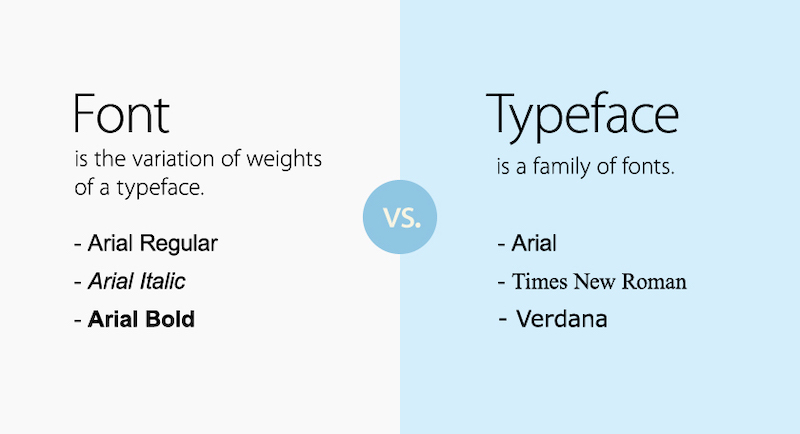
2. Phân biệt các font chữ thông dụng
Bạn không cần phải biết quá nhiều font chữ, nhưng những phông chữ phổ biến dưới đây bạn cần phải nắm rõ để có những lựa chọn tốt nhất cho website của mình.
2.1 Font chữ Serif
Font chữ này được đặt mặc định ở rất nhiều công cụ bởi sự đơn giản dễ nhìn. Đặc điểm dễ nhận thấy nhất của phông Serif này là có các nét gạch ở dưới chân hoặc trên đầu một vài ký tự.
So với các phông chữ khác, Serif thanh mảnh, ưu nhìn và phù hợp sử dụng trong hầu hết mọi trường hợp. Và đó là lý do, Serif là font chữ phổ biến nhất, xuất hiện hầu hết trên những website báo chí hoặc sử dụng cho các trang blog.
2.2 Font ký hiệu
Chắc chắn, khi sử dụng Words bạn đã bắt gặp webdings, wingdings… đây chính là font ký hiệu (symbol). Font ký hiệu mang nhiều giá trị về mặt trang trí, tượng trưng hơn là giá trị truyền đạt văn bản.
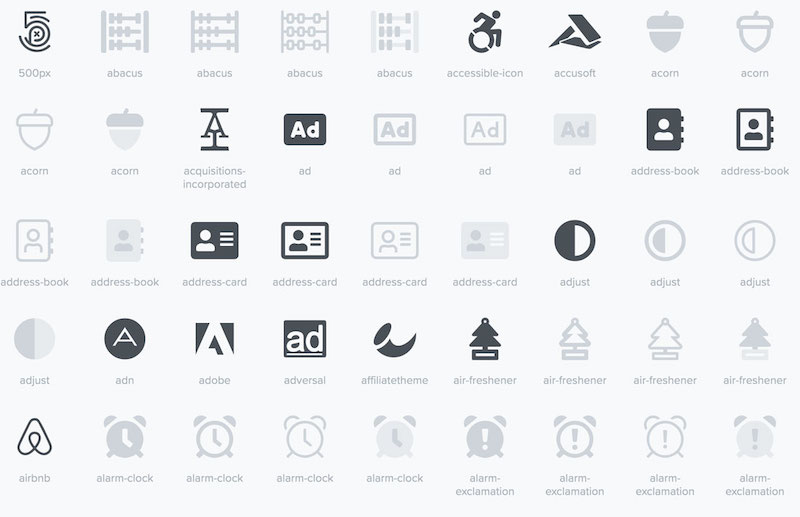
2.3 Font chữ phá cách
Khác với font chữ cơ bản Serif, phông chữ phá cách – Display là với những đường nét hiện đại, tinh nghịch, không bị gò bó trong khuôn mẫu chuẩn mực nào cụ thể. Font Display này sẽ phù hợp với các banner quảng cáo, ấn phẩm, tờ rơi. Còn nếu là trang web thì phải là những website mang tính nghệ thuật rất cao mới hợp sử dụng font chữ này.
2.4 Font chữ Script
Script có nét mảnh, mềm, giống với nét viết tay, phù hợp với thiệp mời, những văn bản chia sẻ, tâm sự… Ngoài ra, những website làm về lĩnh vực làm đẹp, thẩm mỹ, mỹ phẩm cũng rất hợp sử dụng phông chữ này trên các banner khuyến mãi.
3. Những font đẹp cho web
Nếu bạn chuẩn bị thiết kế website và đang muốn tìm một font chữ đẹp cho web, dưới đây là những cái tên mà bạn có thể tham khảo.
3.1 Arial – Font đẹp cho web
Cái tên đầu tiên cũng là font chữ vô cùng quen thuộc đó là Arial. Phông chữ này được nhận định là phông chữ rất an toàn và phù hợp với hầu hết các ngành nghề. Sử dụng Arial, bạn có thể yên tâm các văn bản sẽ được trình bày 1 cách rõ ràng, dễ đọc, khoảng các chữ vô cùng hợp lý, vậy nên khi khách hàng theo dõi 1 bài viết dài cũng không cảm thấy bị mỏi mắt, khó chịu.
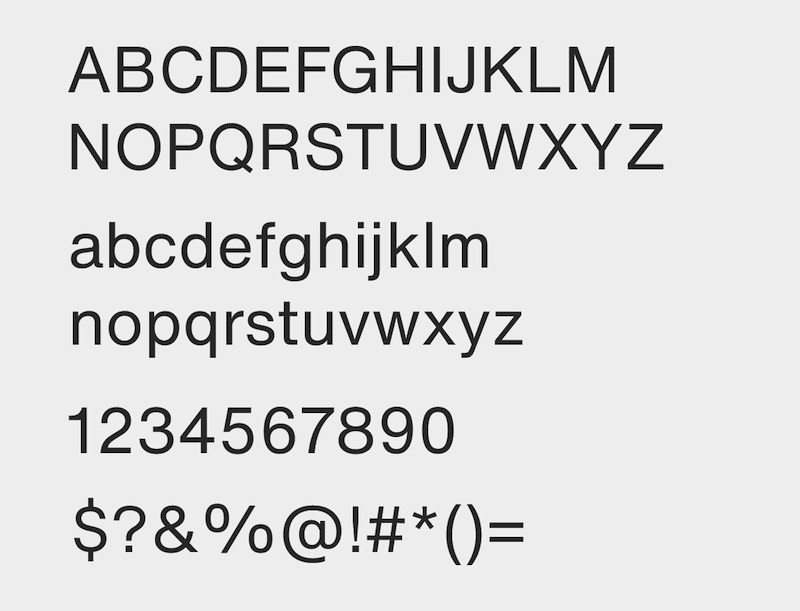
3.2 Time New Roman
Một font đẹp cho web bạn nên tham khảo là Time New Roman. Đây là một trong những font xuất hiện từ rất lâu nhưng vẫn có tính ứng dụng cao. Đặc điểm của font đẹp cho web này là các nét nhìn khá chuyên nghiệp, hiện đại nhưng cũng không kém phần mềm mại. Hầu hết người dùng đều đã rất quen thuộc với Time New Roman vậy nên bạn có thể cân nhắc font chữ này cho 1 số hạng mục trên website của mình
3.3 Courier new – Font đẹp cho web
Cũng là một trong những font chữ đã xuất hiện từ lâu, tuy nhiên đến thời điểm hiện tại vẫn rất nhiều sản phẩm sử dụng font Courier new, trong đó có cả thiết kế website. Khoảng cách các ký tự của Courier new rất lý tưởng, form chữ nền mại, dễ nhìn, dễ đọc. Vì thế, nhiều website lựa chọn Courier new cho các trang blog của mình.
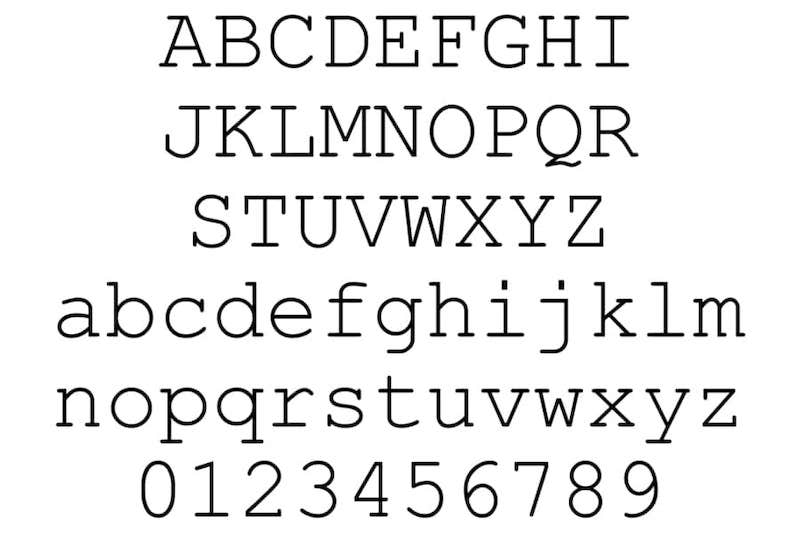
3.4 Helvetica – Font chữ đẹp cho web
Khác với Courier new là các chữ đầy đặn, khoảng cách xa thì Helvetica sở hữu form cao, khoảng cách hẹp hơn, tạo cảm giác chỉnh chu, chuyên nghiệp. Tính ứng dụng của Helvetica khá cao, bạn có thể bắt gặp Helvetica ở bất cứ đâu không chỉ trên các thiết kế web mà còn ở các ấn phẩm quảng cáo.
3.5 Verdana – Font chữ đẹp
Dành cho những ai thích Helvetica nhưng muốn nới rộng khoảng cách giữa các chữ thì font Verdana đáp ứng được yêu cầu này. Các nét mảnh nhưng không hề khó nhìn, tạo cảm giác thoải mái cho người đọc. Font đẹp cho web Verdana rất hợp để xuất hiện trong các site về ẩm thực, đặc biệt là mục menu.
3.6 Georgia – Font chữ thiết kế web đẹp
Georgia nhìn qua sẽ thấy khá giống Time New Roman, nhưng nếu để ý một chút sẽ thấy kích cỡ các chữ to hơn, chân chữ cũng rõ nét hơn, các nét cũng đậm hơn, tròn hơn. Và nếu xếp hai font chữ này lại với nhau bạn sẽ thấy sự không ăn khớp.
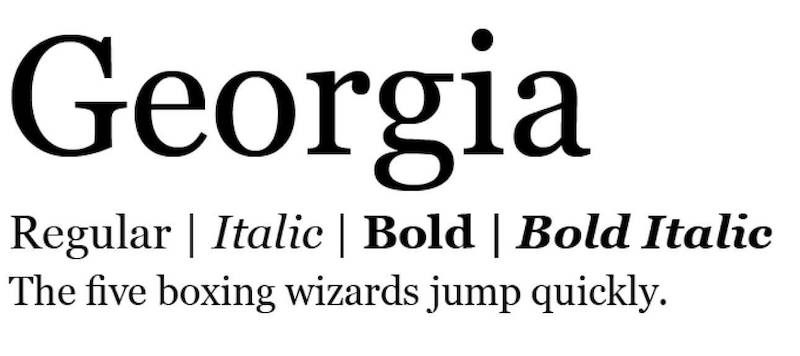
Ngoài 6 font đẹp cho web kể trên, bạn có thể tham khảo thêm 1 vài font chữ thiết kế web cũng khá phổ biến khác như Bookman, Garamond, Calibri, Tahoma… Đây cũng đều là những font đẹp, bạn có thể xem tính chất, đặc điểm từng font để cân nhắc sử dụng cho thiết kế web của mình. Và đừng quên theo dõi các bài viết trên blog Sapo.vn để có thêm nhiều kinh nghiệm về thiết kế website nhé.